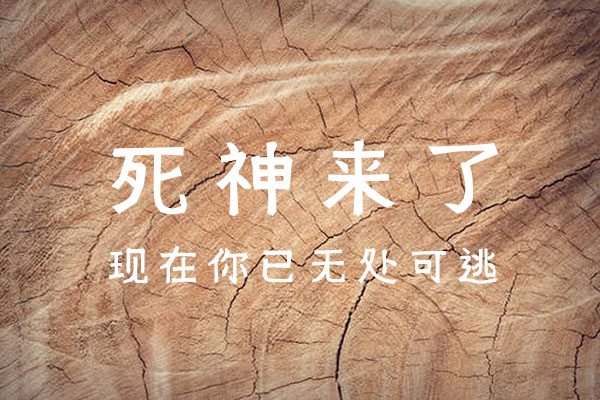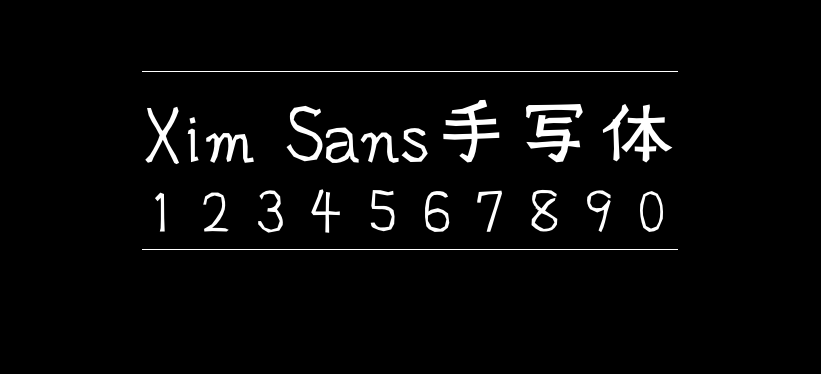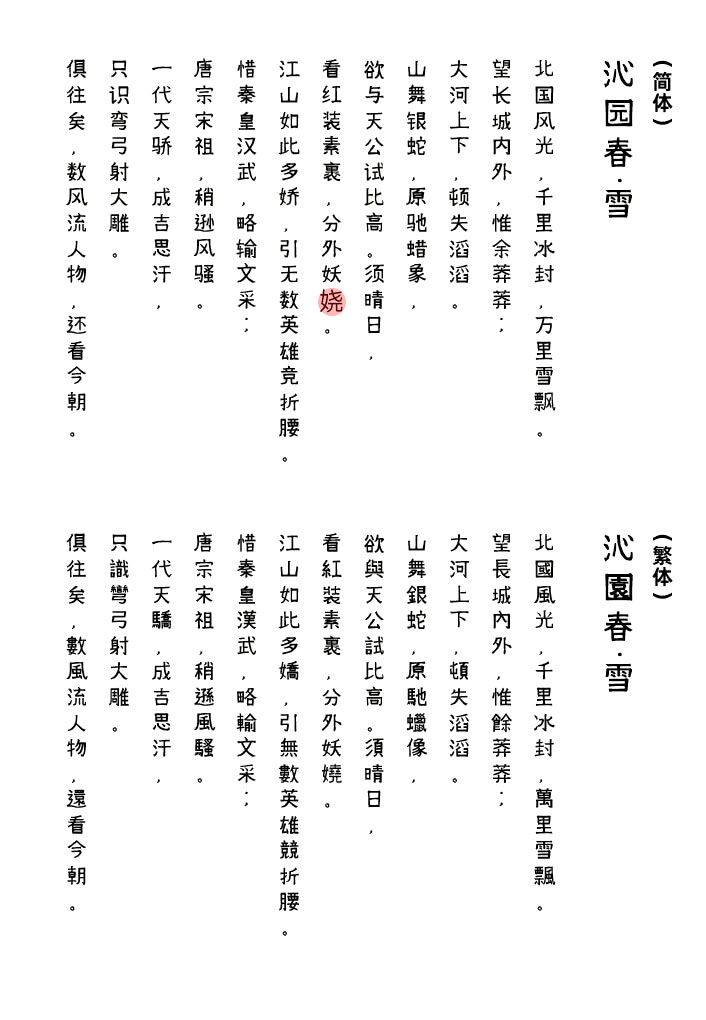
Xim Sans手写体
Xim Sans手写体(Xim Sans Handwritten 、 Xim Sans 手書き風)是日本设计师ximco创作的一款免费商用手写字体。这款手写字体的风格,据作者自己称“是一种嘎嘎作响的字体,它有一种恐怖的味道”,感觉像是干枯的手骨在木板或者钢板上划过的痕迹。
Xim Sans手写体现已收录43,345文字,作者的目标是世界上记录字符数最多的字体!目前来看确实字符很多,虽然自由字体将该字体归类为日文字体,但实际上简体和繁体基本都不缺字,大家可以放心下载使用了!
Xim Sans手写风格(英文字体名称:Xim Sans Handwritten)
现在的版本是ver1.32。
现在的收录字数:43,345字
~~~~~~~~~字体的介绍
是手绘风格的某处以硬朗的形状为特征的TrueType字体。
根据使用方法的不同,还会有恐怖的味道吗?
另外,因为收录了很多的文字各种各样的语言的标记也能使用! !
同捆的Xim Sans Brahmic是印度系文字特殊化的字体。(实际上是日本产的字体中唯一能显示tilfta / mytili文字的)
因为现在进行时收录的文字的数量在增加所以升级的时候会依次告知。
不断追加Unicode中存在的文字和不存在的文字。
现在除了通常的ASCII文字和日语中使用的汉字、假名以外,还收录了以下文字。(详情请参考附件“ver1_32.txt”。)
中文(普通话、广东话)等使用的汉字(一部分)
·数学符号、几何图形、技术符号等
·带有高分子标记的拉丁字母
韩文(部分)
·泰国文字、老挝文字、缅甸文字、高棉文字
·代瓦纳加利字母、孟加拉字母、古尔穆基字母
绘文字
等等。
另外,Unicode中不存在的文字也被追加到私人领域。详情请参照附加的“Xim Sans Unicode未注册字符的解说_1.32”。
~~~~~~~~~~ ~~这次的变更点
·改变了在私用区域的西里尔文字的扩展文字和定形阴影用图形的代码位置。
·将在私用领域中剩余的Unicode图画文字中存在的国旗全部追加,通过regional indicator symbols的连接来显示。
·在私人领域追加了海图用记号,satelnotse, TRPG用多面体骰子的图画文字,保加利亚语用西里尔文字等。
北极熊的图形(?‍❄)帮标准的合成从文字标识可能。
·ipa的声调符号连接中声调的升降级这些符号(˥˩˩˥等),显示可能的(3文字的连接是˥˧˥˥˩˧˦˥˦˦˨˦˧˥˧˧˥˩˧˩˥˧˩˧˧˩˨˨˩˦˨˩˨˨˦˨˩˥˧˩˧˩只对应)
·其他,追加以下文字。
㖘㶞㹫䵥憢槚猉獑穚簆臜荈菈菭萙蔎螉賖赩輘輷閗靘騀鹐ꀵꁅꁝꄁꄂꊐꋪꌹꌺꏣꐁꐂꒈꒉ섪쯕쯖쯗쯘쯙쯚쯛쯜쯝쯞쯟쯠쯡쯢쯣쯥쯦쯧쯨????????????????????????????
·古,韩文,ᄋᆢᄃᆞᆸᄯᅥᄯᅥᆨ显示可能。
·修改了泰文、拉奥文、希伯来文的文字宽度。(叛逆的人)
·僧伽罗文字是一部分合字,kanada文字是最小限度的子音簇的标记。(由叛逆之人修正)